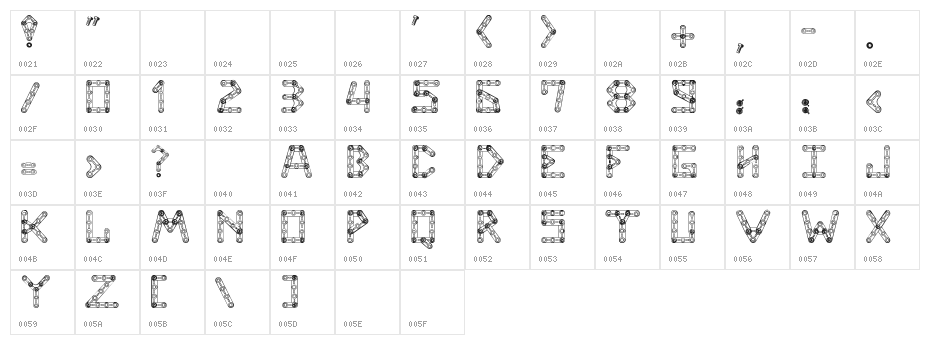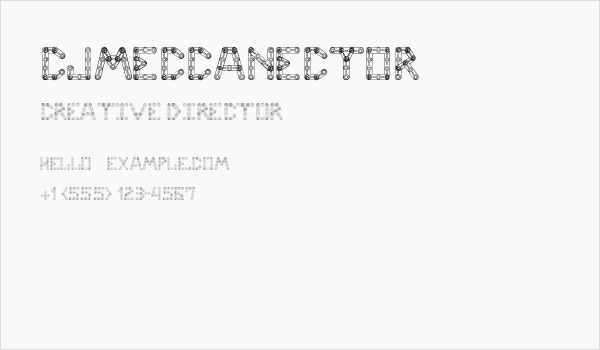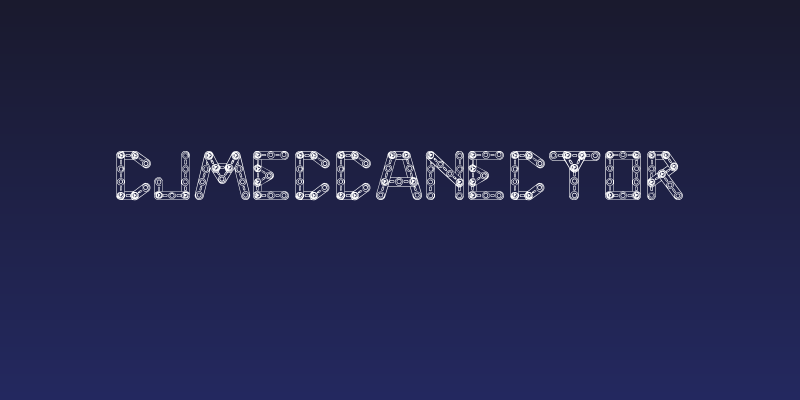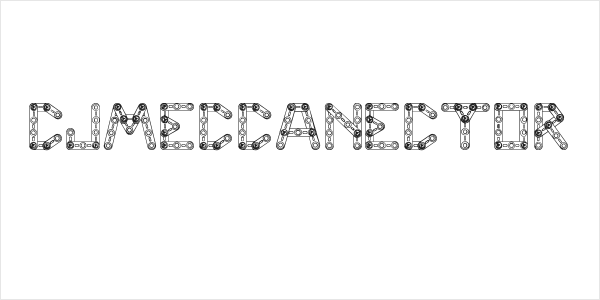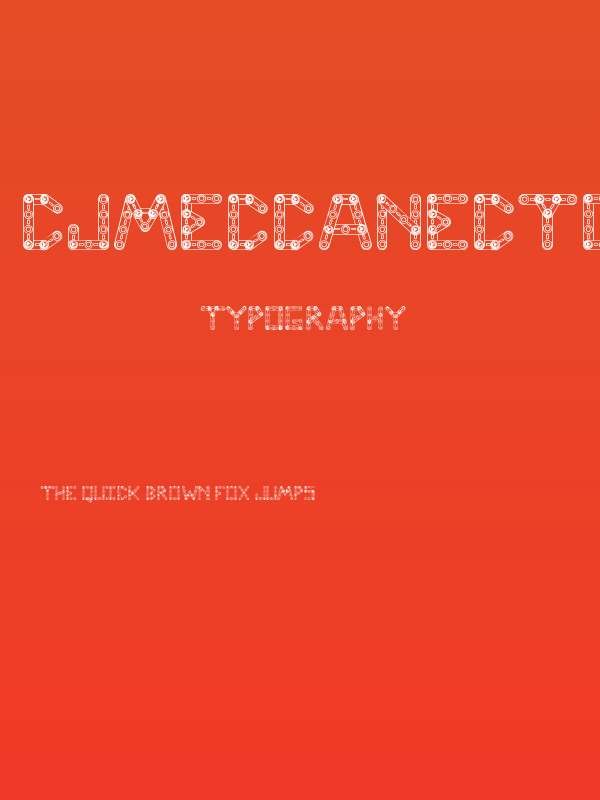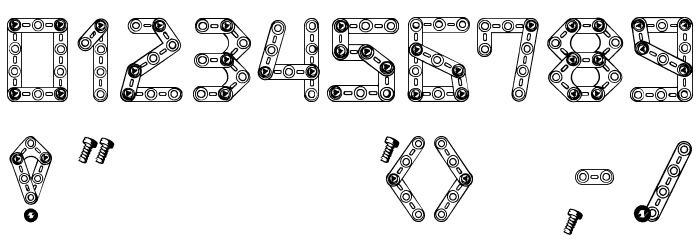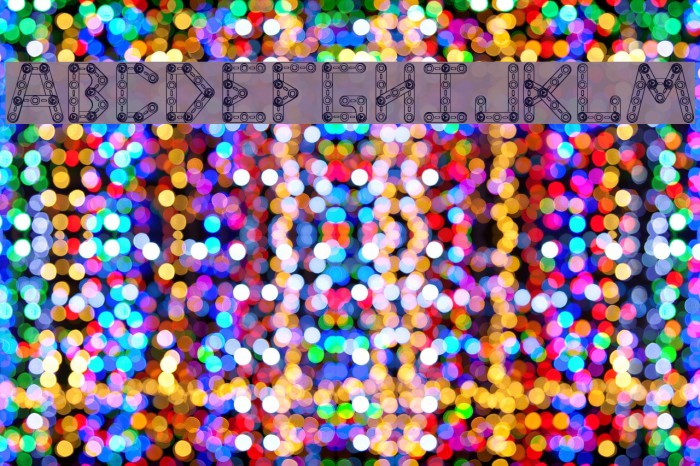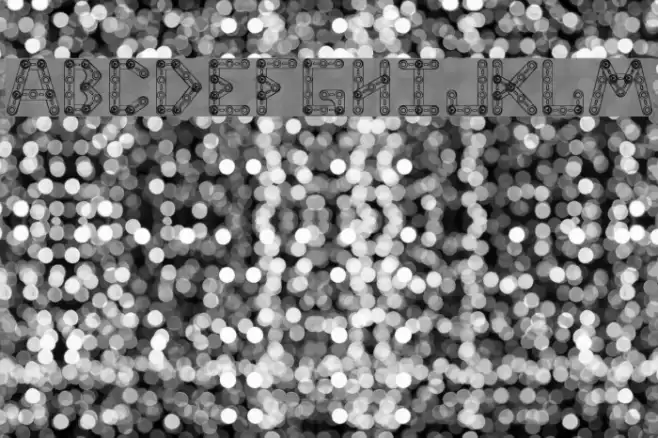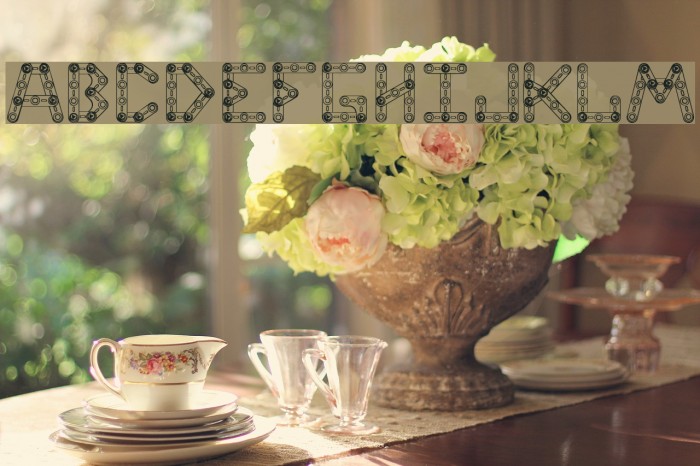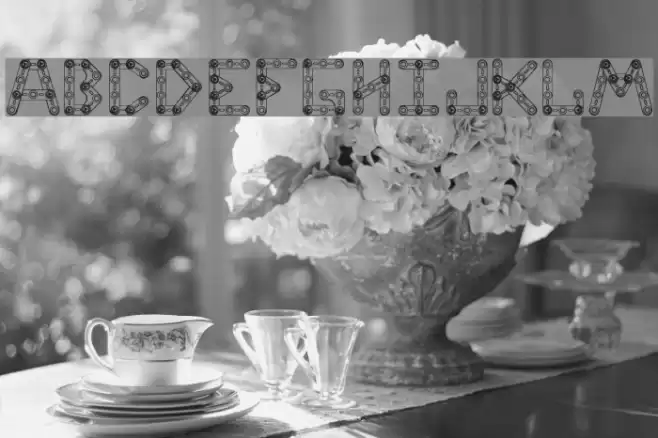
CJMeccanector Font
| 全体的なスタイル | Industrial, Playful |
| 用途 | Logos, Posters, Branding |
| おすすめプロジェクト | Ideal for engineering-themed posters, technology branding, construction company logos, and educational materials related to mechanics. |